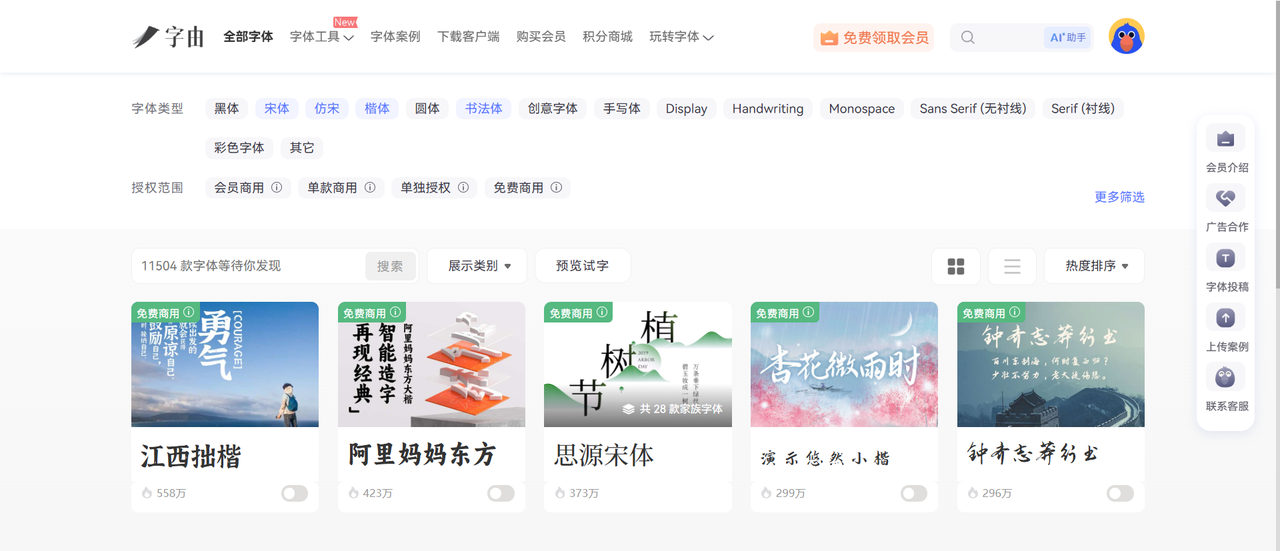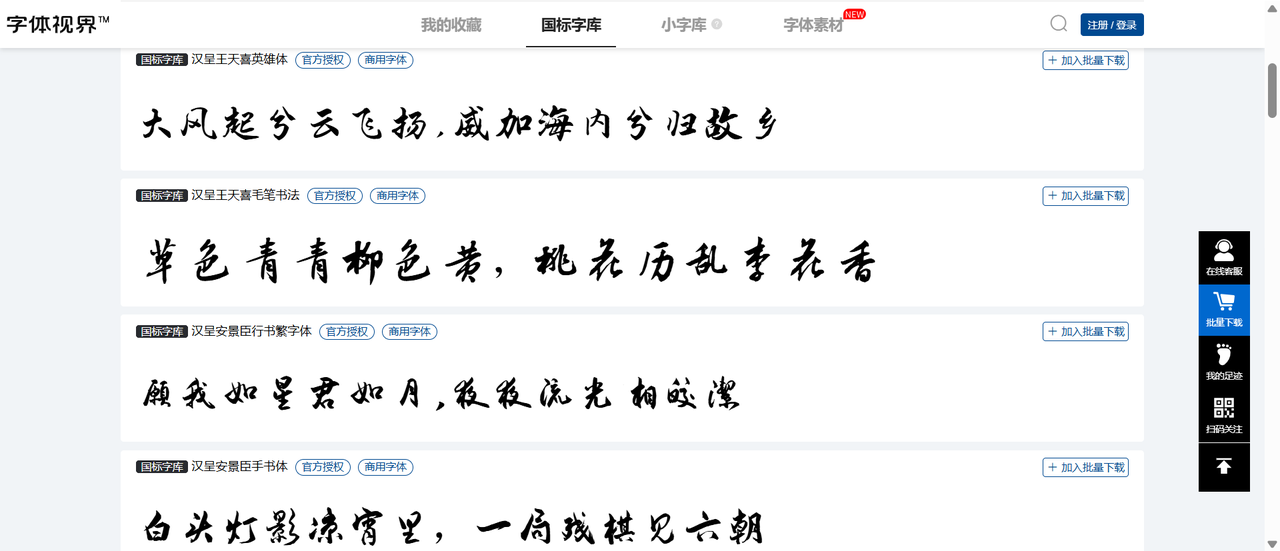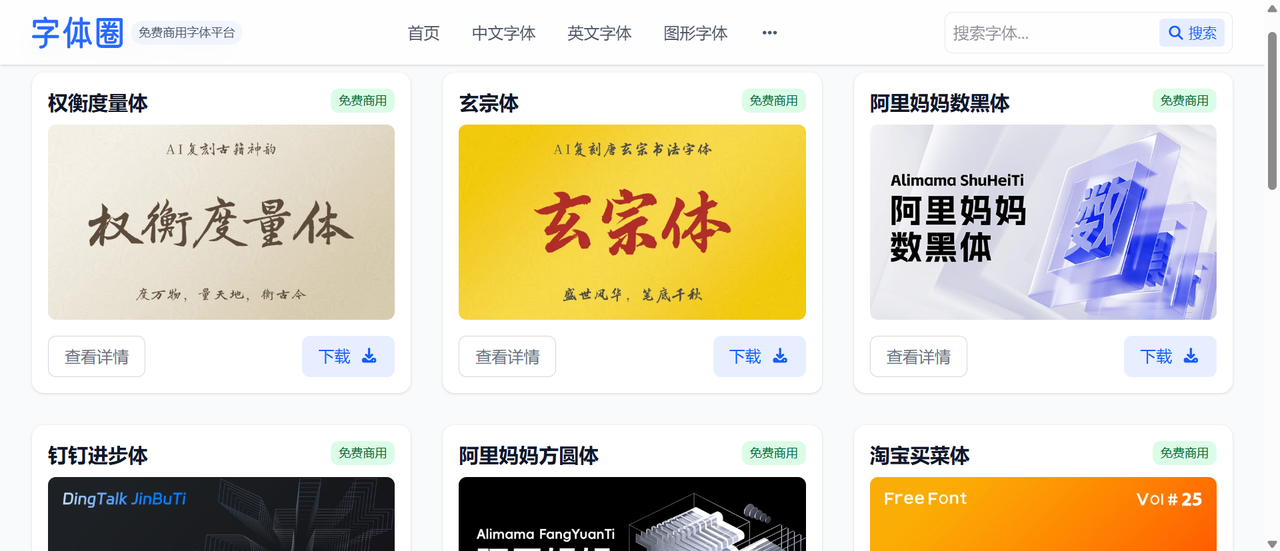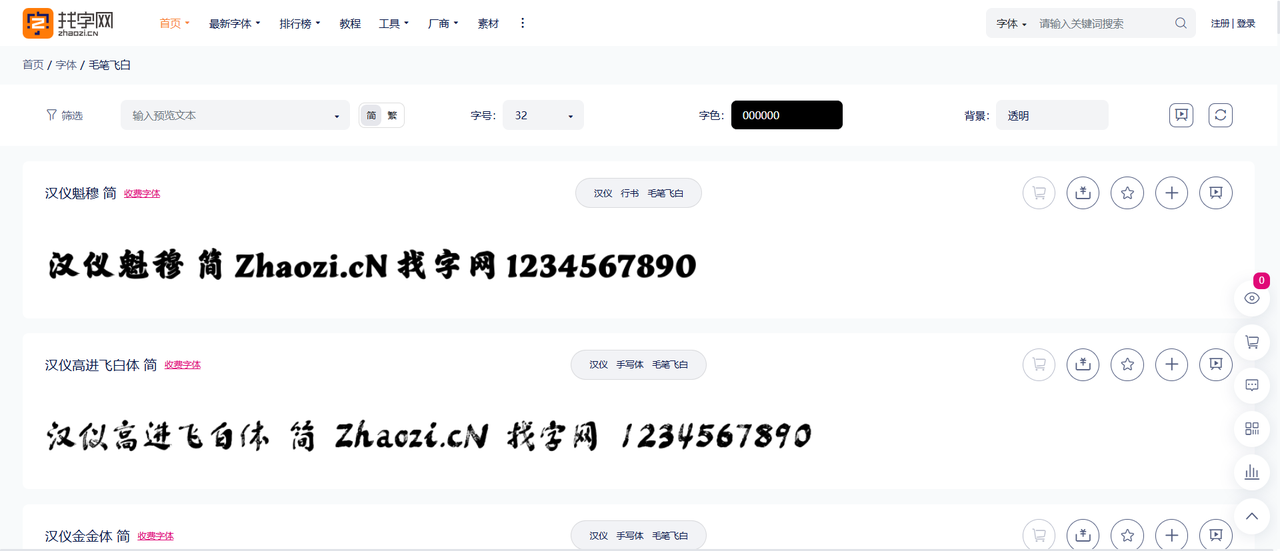
2026年ps毛笔字体免费下载和使用教程!新手可用
无论是在设计海报,宣传图还是打造品牌视觉时,毛笔字体同样可以帮助我们营造具有传统东方美感的设计效果。它笔画变化丰富,能呈现出优雅的艺术氛围,在多种设计场景中都是必不可少的字体。但在下载毛笔字体,尤其在将毛笔字体应用到 PS 中时,很多朋友就会犯难。别着急,本文已经整理好了详细可用的 PS 毛笔字体免费下载和使用教程,对于新手设计师来说也十分适用,一起来看吧!
一、PS 毛笔字体下载网站推荐
1、字由:适合PS设计使用的毛笔字体管理工具
字由是想为大家推荐的第一款下载毛笔字体的网站,无论是对于专业设计师,还是新手设计师来说,字由都是一个既方便,又高效的字体使用助手。
它站内汇集了上万款不同类型,不同语言的字体素材,其中还包括 3000+ 款拥有公开授权的,支持免费商用的字体素材。如果你的毛笔字体要用于商业设计,那么字由将为你规避掉作品侵权的风险,让你来充分发挥自己的创意。
虽然字体丰富,但在字由中查找字体时并不麻烦,字由还提供了预览功能。对于书法字体来说,字由是做出了更细致的分类,将毛笔字分为了宋体,仿宋,楷体,圆体,如果你需要更加有设计感的字体,也可以选择书法体。当然,无论哪款字体,字由都为你提供正版字体。
2、字体视界
字体视界站内包含黑体、宋体、楷体、毛笔书法等多个字体分类,你根据不同的项目需求来寻找字体素材。在 PS 设计过程中,毛笔字体经常用于标题、品牌视觉、传统文化主题海报等场景,因此字体风格和授权情况同样重要。而字体视界除了提供字体浏览,也提供了字体相关授权服务,方便你更直接地了解到字体使用范围。
3、字体圈
字体圈站内提供的主要是中文字体,其中就包括我们今天要用到的书法字。我们访问网站后,可以先使用关键词 “书法字”, “手写字体” 等来筛选查找。
同样,字体圈也提供了字体预览功能,我们在下载字体前,可以先预览具体的字体使用效果是否真的符合我们的设计主题,要根据设计主题来挑选合适的字体使用。选择字体后,再将字体下载保存到本地,后续就可以在 PS 中直接调用了。
4、找字网
在制作具有传统文化感的设计作品时,毛笔字体的风格差异会直接影响最终效果。比如有些作品需要苍劲有力的笔触,有些作品则需要更加自然柔和的书写感。而找字网支持你按字体风格来挑选毛笔字体,快速找到适合你作品的毛笔字体。
5、字体侠
字体侠中的字体分类较丰富,你可以根据自己的作品需求来寻找具有书写感或者艺术表现力的字体。或者当你需要完成多种设计工作时,同样可以来字体侠中查找字体,将它作为 PS 的字体素材库。
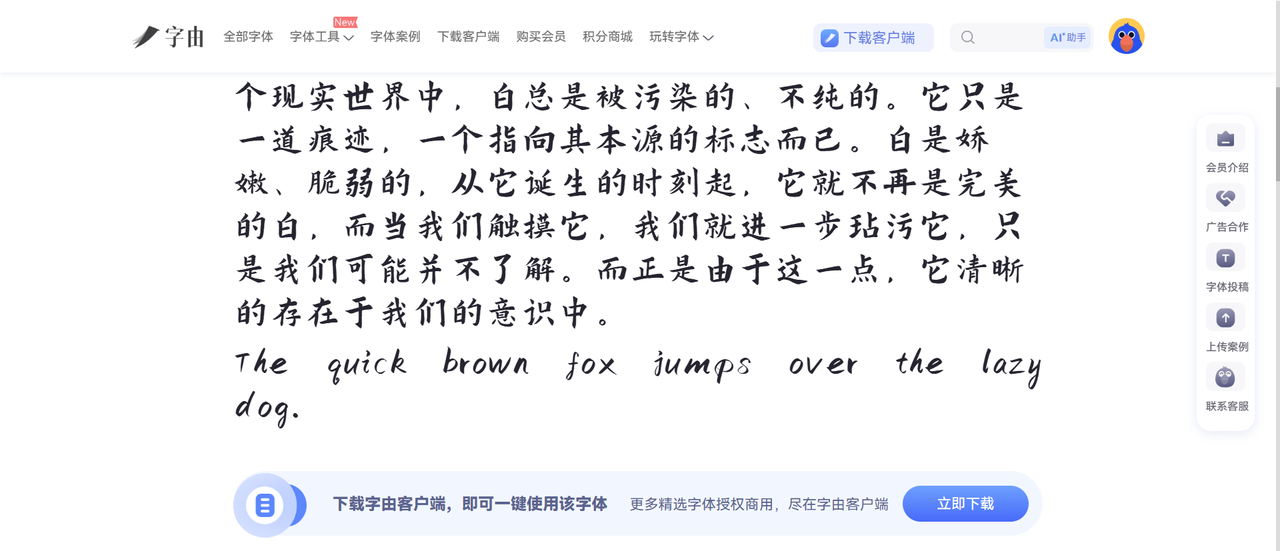
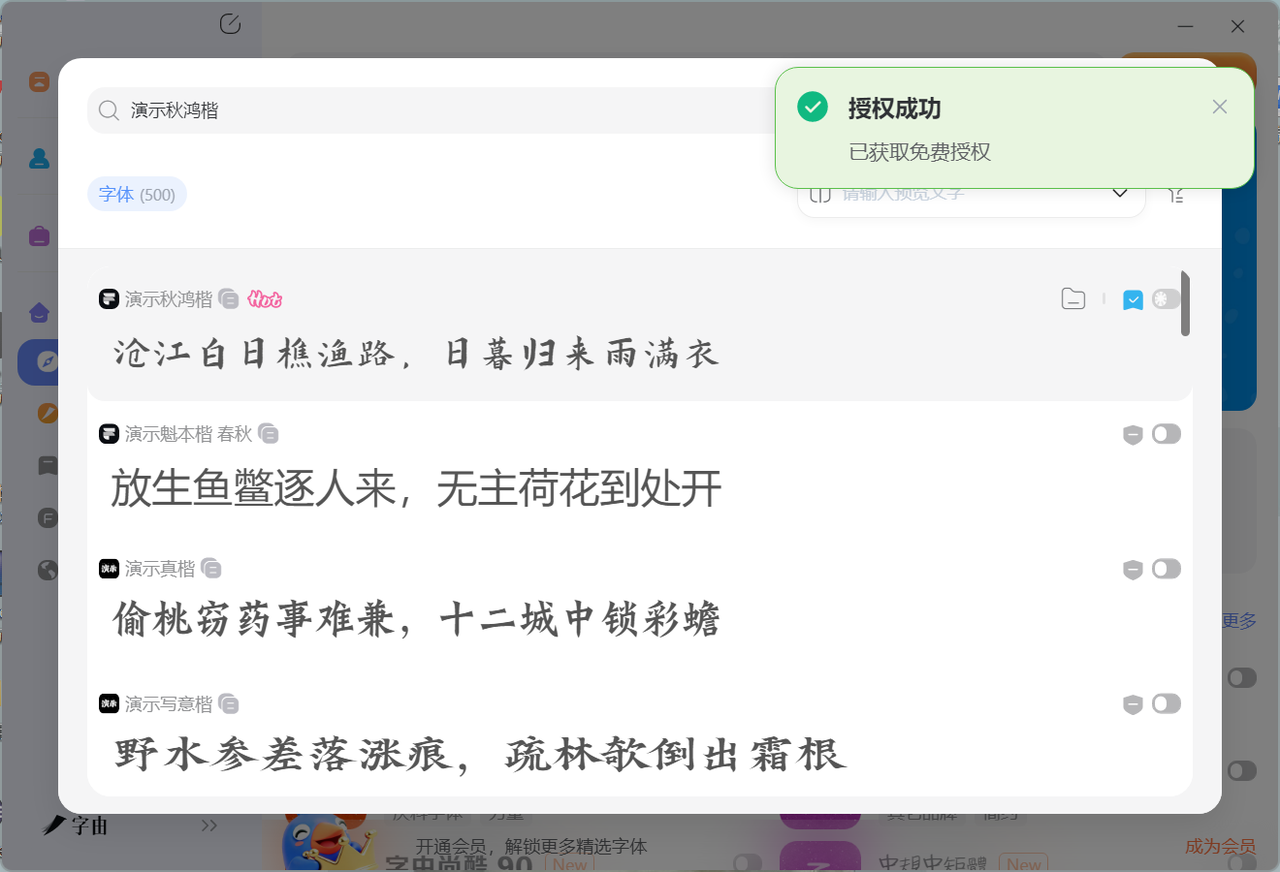
合适的毛笔字体是提升设计作品视觉效果的重要因素,所以在选择字体时,我们应该从作品的设计主题出发来选择字体。如果感觉没有太好的毛笔字体使用灵感,那么可以来看一下字由的【字体案例】版块,这里已经按照设计场景为你搭配好了在不同的设计场景下可以使用什么类型的字体,希望能为你带来一些灵感。